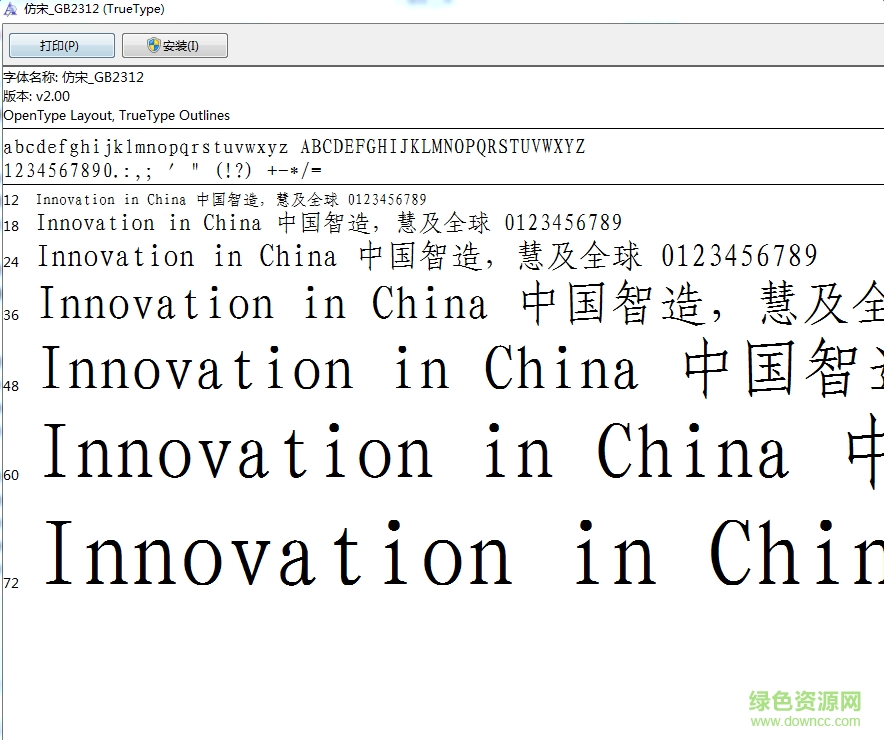
simfang字體是一款時(shí)尚文雅風(fēng)格英文字體軟件,simfang體筆畫細(xì)膩工整,在英文字方面有著不錯(cuò)的應(yīng)用,整體效果非常清爽醒目,還有更多好看字體歡迎來綠色資源網(wǎng)下載體驗(yàn)!
simfang仿宋字體2312,是一款比較常用的字體,該字體筆畫細(xì)膩,尾部的甩尾有力且有豐富的筆觸細(xì)節(jié),大字效果突出且引人注目;并且最大程度還原作者書寫字形,細(xì)節(jié)表現(xiàn)完整,且字庫完整,可以廣泛應(yīng)用于名片設(shè)計(jì)、新聞媒體、宣傳海報(bào)、ppt、影視制作以及內(nèi)容用字等領(lǐng)域。